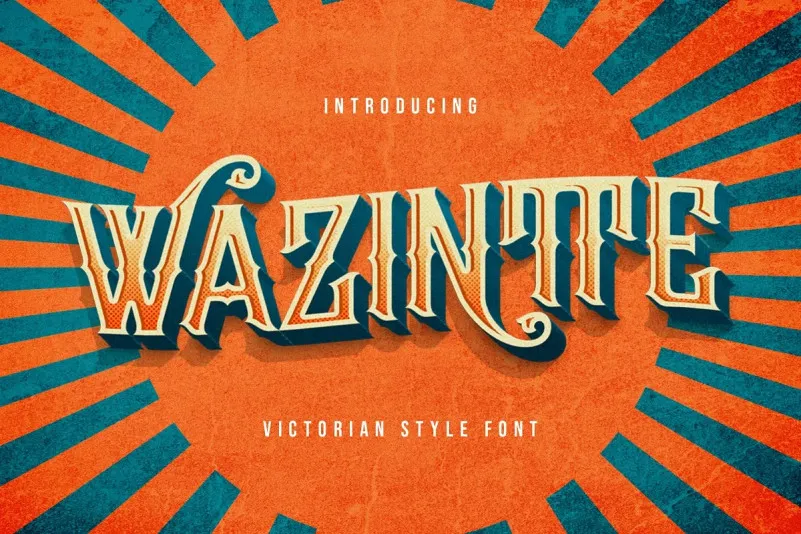
A Wazintte é uma exuberante fonte de display inspirada na arte vintage do tatuagem, criada pelo designer StringLabs para a plataforma 99designs. Sua essência vintage e nostálgica ganha vida por meio de formas românticas e poderosas, que não apenas lembram o passado, mas também entregam um encantador visual de época. Esta fonte se destaca por sua versatilidade em designs modernos e clássicos. Seja em uma publicação vintage retrô ou em um projeto de design contemporâneo minimalista, Wazintte transmite seu fascinante aspecto vintage. Suas características meticulosamente detalhadas garantem que cada letra seja perfeita e atraente. É perfeitamente adequada para aqueles desejando uma fonte com uma sensação vibrante de nostalgia, ideal para aplicar em um design digital de moda vintage ou em gráficos para o mundo físico. Wazintte traz uma dose de charme vintage ao seu projeto, tornando-a a escolha perfeita para quem busca um visual de época que também é moderno e atraente.